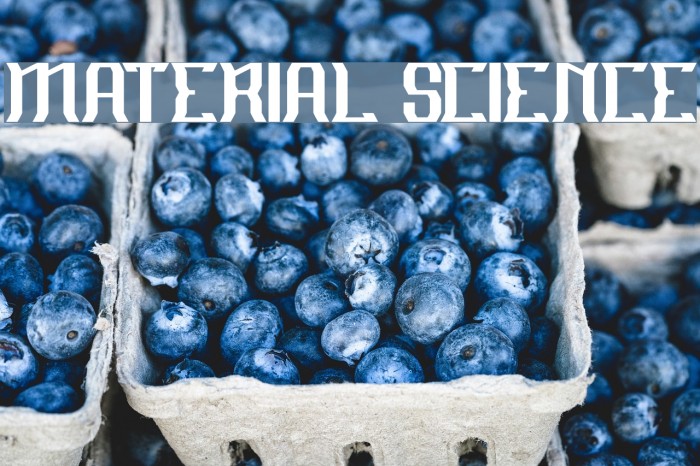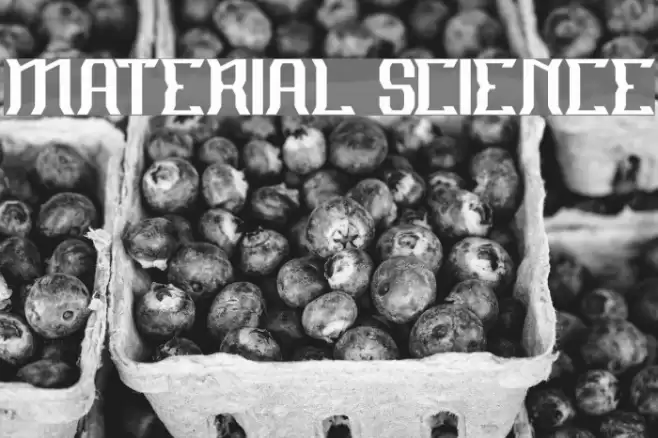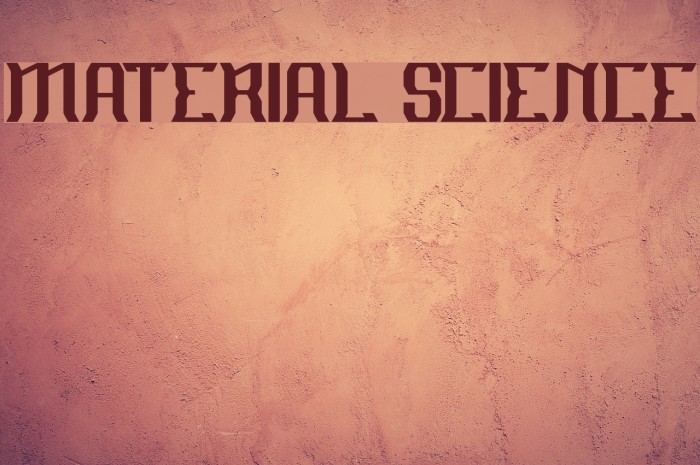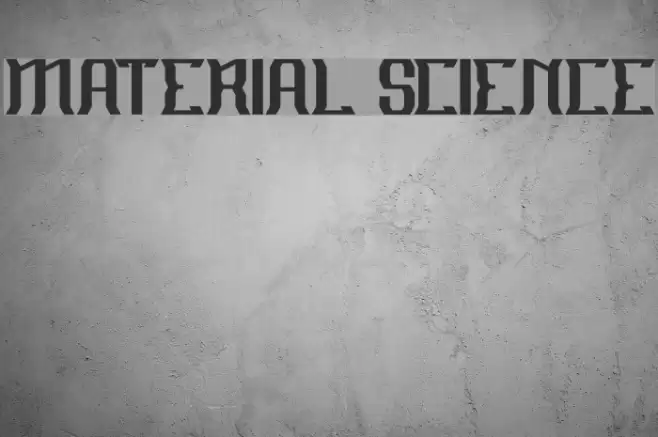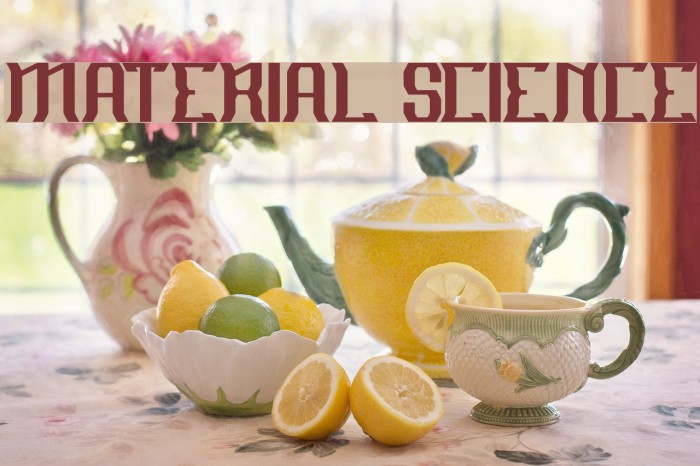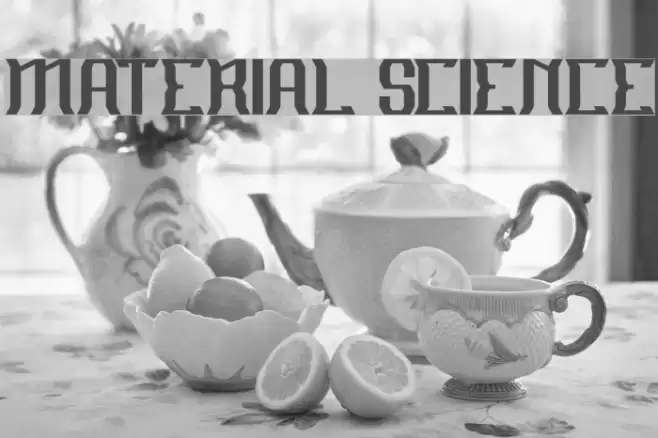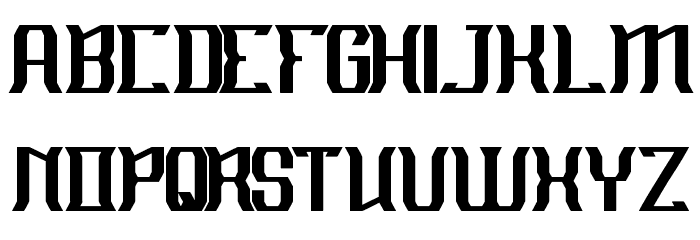
MATERIAL SCIENCE Font
✎ Thick
| Categorías | Thick |
| Caso de uso | Logos, Headlines, Posters |
| Proyectos propuestos | Ideal for branding, logos, posters, and any project requiring a modern, industrial aesthetic. |